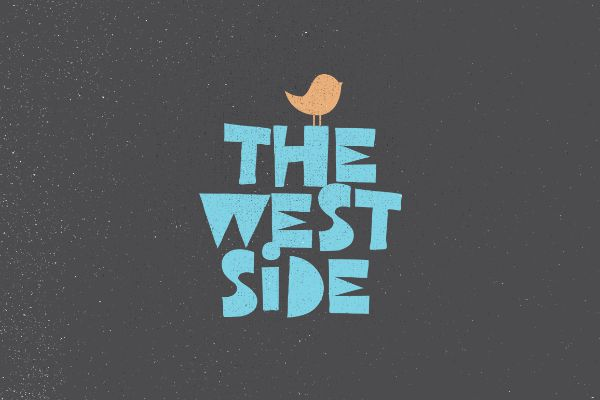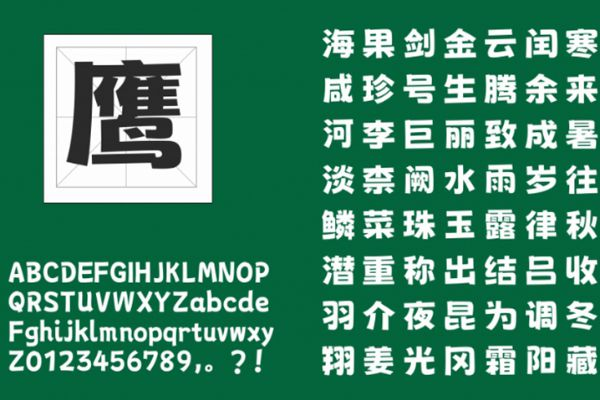
可爱字体可以商用吗?10 款免费好看的可爱字体
可爱字体并非一个独立的“字体家族”,它是一种字体风格。一提到“可爱字体”,你脑海中是不是立刻浮现出那些圆润、俏皮、带着一点点手绘感的字形呢?没错,可爱字体正是这样一种能瞬间点燃我们内心童真与温暖的字体类型。本文就给大家介绍 10 款免费好看的可爱字体。
可爱字体的使用场景
- 玩具包装、童装宣传。一些和孩子“玩”相关的场景,可以使用一些可爱字体,作用非常直接,吸引小朋友的目光。
- 儿童绘本、早教App。一些和孩子“学习”相关的场景,能让学习过程变得更有趣,减轻孩子的学习压力,激发他们的兴趣。
- 零食、饮料包装。说实话,我也会因为这些可爱的包装所吸引,然后下单!
- 手账、日记、贺卡设计。 增添一份手作的温度和独一无二的可爱。
- 结婚、满月宴、毕业典礼等请柬。让邀请函充满喜悦和温馨,让被邀请人感受到是一个轻松愉快的聚会。
10 款可以免费商用的可爱字体!
WestSide
WestSide是一款具有强烈复古风格和独特个性的字体。粗犷的笔触、棱角分明的造型,融合了美国西海岸文化、街头艺术等元素,让它非常适合潮流和流行的相关设计。在一些音乐专辑封面、潮流服装品牌Logo、街头艺术作品、滑板文化宣传中非常的适合。
荆南波波黑
荆南波波黑是一款融合了现代审美与亲和力的黑体字体。其笔画饱满圆润,字形结构稳健,整体风格简洁大气,在保持黑体字清晰易读优势的同时,增添了一份独特的柔和感。
比较适合用于品牌标识、广告海报及网页排版,能够有效提升设计整体的现代感和辨识度。
xiaoheigungunti
xiaoheigungunti是一款充满个性和手绘感的字体。其笔画仿佛用随性的小黑棍描绘而成,不拘一格,充满自由与活力,带有强烈的手写温度。适合用于创意设计、个性签名以及社交媒体内容,能够表现独立的个性。
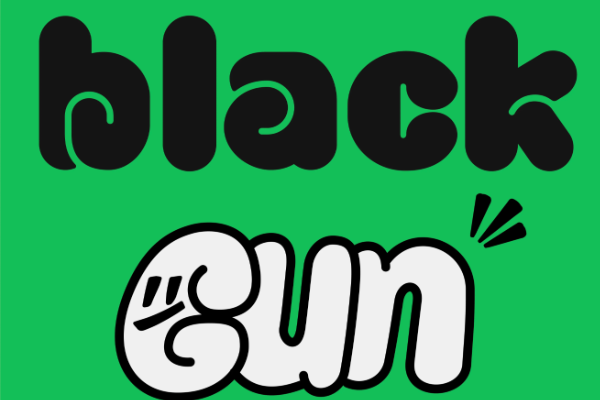
呆萌手写体
呆萌手写体是一款以可爱、萌趣为主要特征的中文手写字体。其笔画圆润,字形结构童趣盎然,仿佛出自孩童之手,充满纯真与无邪,能够瞬间拉近与读者的距离。这个是一个比较适合儿童学习类的可爱字体,适用于儿童读物、趣味海报及生活类应用界面,能有效营造轻松愉悦的氛围。
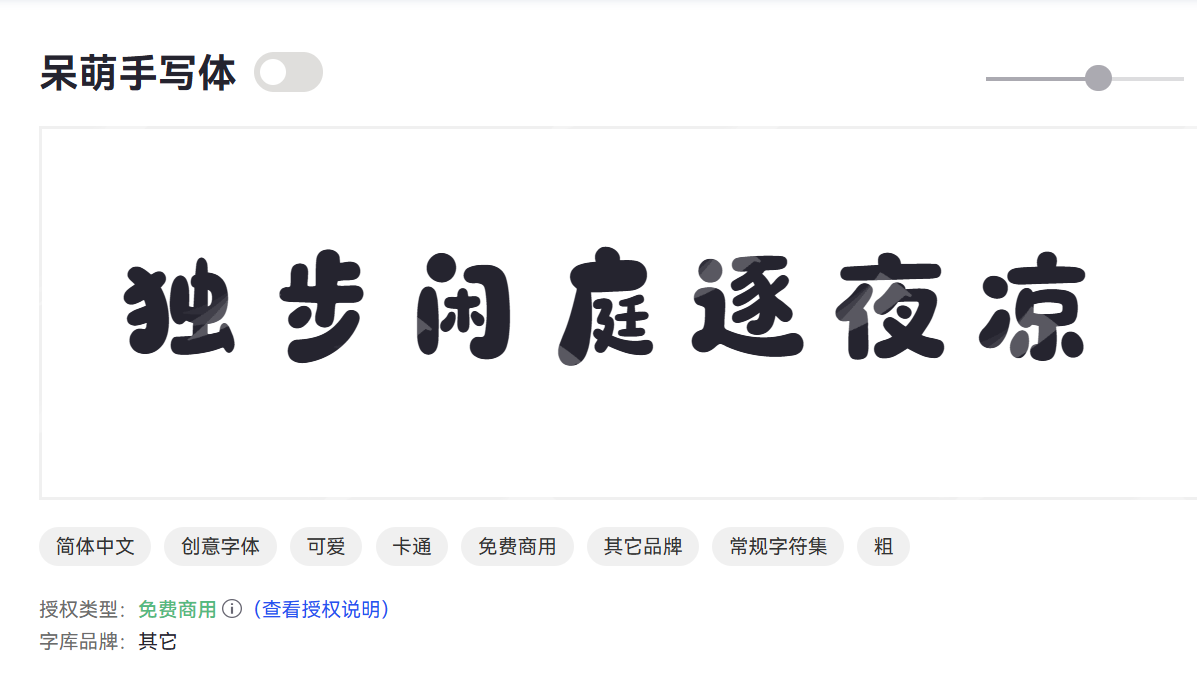
jombie
jombie是一款现代感十足的无衬线可爱字体,其设计风格简洁明了,笔画干净利落,无多余装饰,注重功能性和易读性。适用于品牌视觉、网页设计和产品包装,提升设计的简洁与现代感。
Little Edward
Little Edward是一款优雅且带有复古韵味的衬线字体。适合用于杂志排版、婚礼请柬及精品包装,能够赋予设计作品浓厚的艺术气息和品质感。我曾经在设计一个婚礼H5的时候,就用了这款可爱字体。
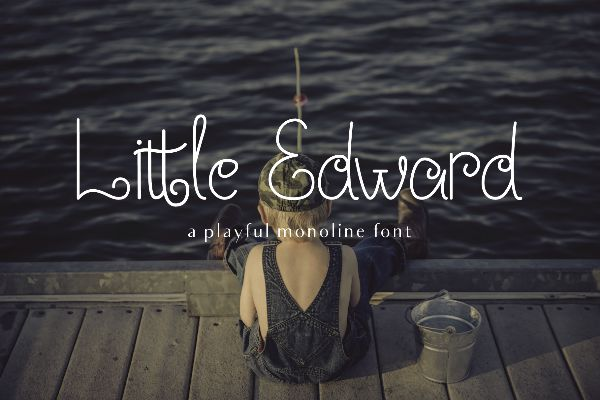
Nishiki-teki
Nishiki-teki是一款充满东方韵味和艺术美感的日式书法字体。其笔触流畅而富有变化,结构灵动且不失雅致。非常适合东方风格的餐厅菜单、文化展览及艺术作品设计,能够彰显独特的和风美学。
Playbox
Playbox是一款充满童趣和活力的手绘风格字体,其笔画粗犷而圆润,字形结构活泼,仿佛是儿童涂鸦或游戏中的文字,能够瞬间激发人们的玩乐之心。和呆萌手写体一样,适用于儿童教育、娱乐节目及游戏界面,能够增强设计中的趣味性和吸引力。
StarLoveSweety
StarLoveSweety是一款浪漫而甜美的手写字体,其笔画纤细流畅,字形优雅,带有心形或星形等装饰元素,整体营造出温馨、梦幻的爱情氛围。
非常适合婚礼设计、情感类产品包装及恋爱主题海报,能够有效传递温馨浪漫的情感氛围。
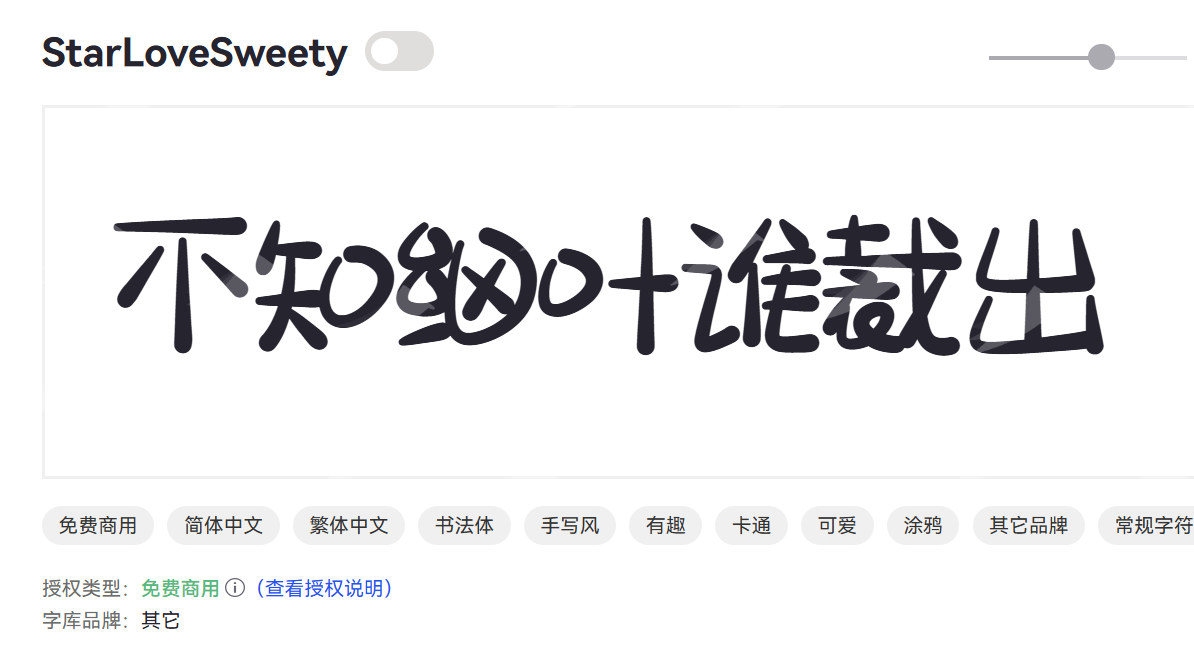
Matemasie
Matemasie是一款现代简洁的无衬线字体,其设计注重平衡、和谐与实用性。适用于企业品牌、网页设计及广告宣传,能够提升设计的专业度和视觉统一性。